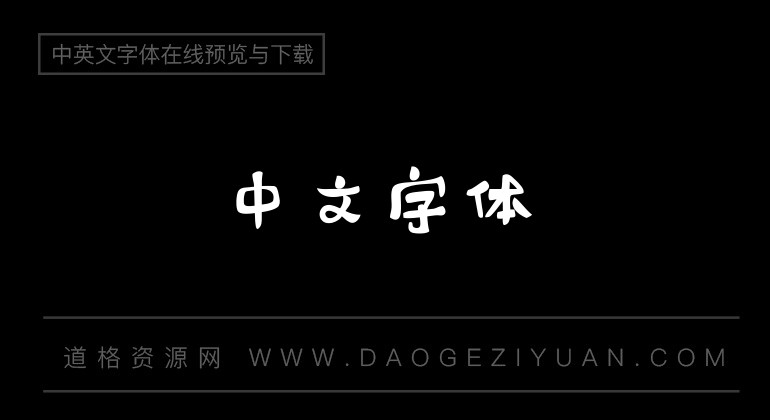
字心坊貓的天空之城P
?字心坊貓的天空之城P是一款字體,它是一款簡約明快的楷體字體,字形線條優美,筆劃流暢,字體大小舒適,讓人感覺清新脫俗。它適用於各種文檔、廣告、網頁、書籍等,可以帶來簡潔優雅的視覺效果,是一款非常適合閱讀的字體。
字心坊貓的天空之城P是一款非常不錯的手寫藝術字體,具有很好的視覺感,適合於文化類的宣傳設計、商業類品牌的廣告和產品包裝設計以及個性化文字排版等較多場景。